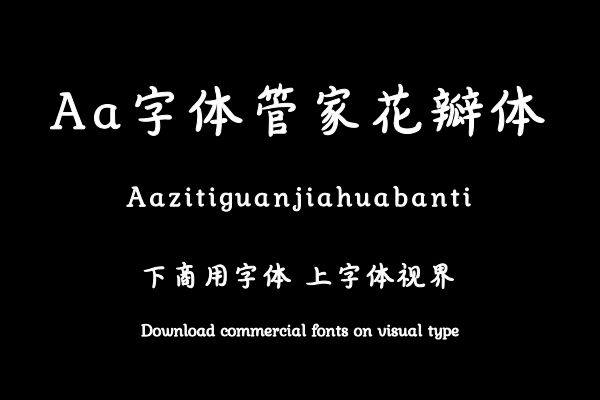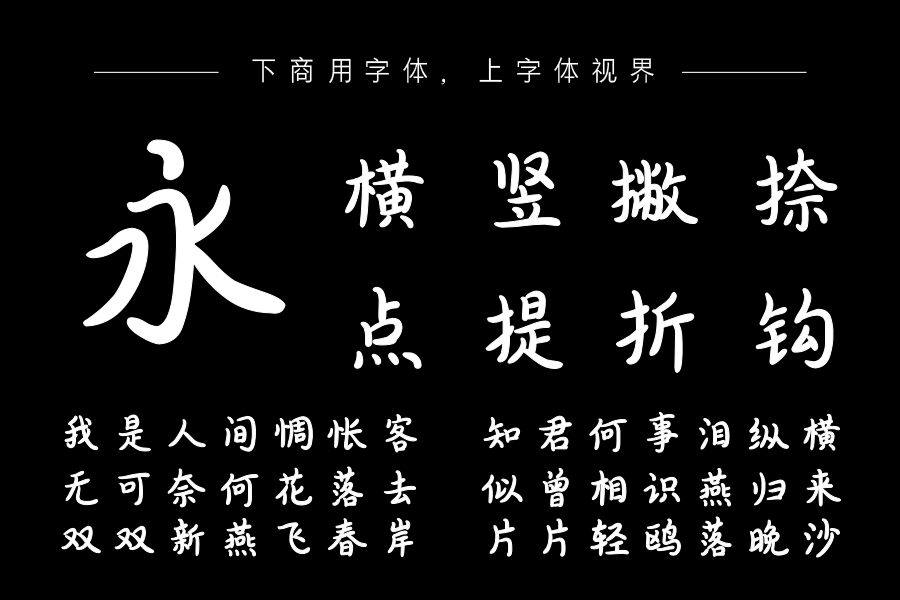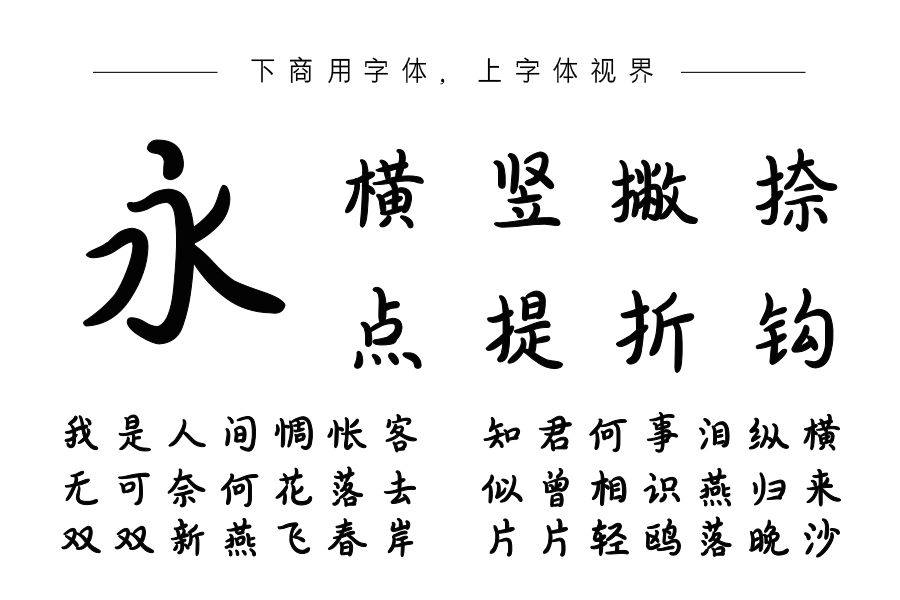
流年的雨点打落的花瓣,是岁月飘零的记忆碎片,每一片都是一个曾经过往的书签。字体以花瓣为原型,笔划柔美,更适合阅读。购买须知:“下载服务费”与“字体VIP”所获得字体 仅用于个人非商用, 商用请联系付费授权。本字体为电脑用字,手机没有root权限不支持直接手机换字(手机如何root,请自行百度搜索教程)。购买前请先 了解清楚后再付款 ,字体为虚拟产品无法回收 一旦购买不支持退款。